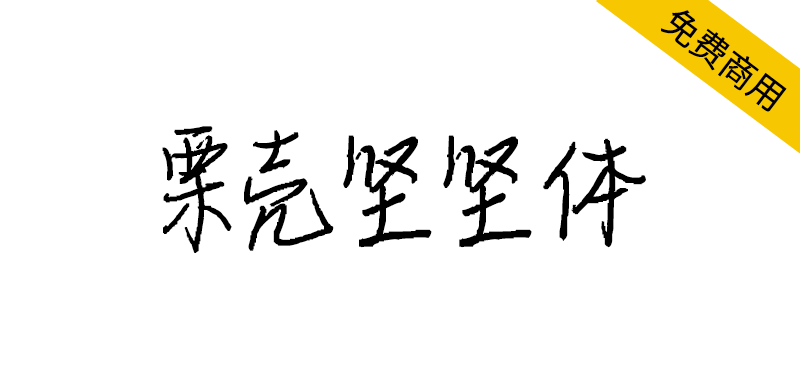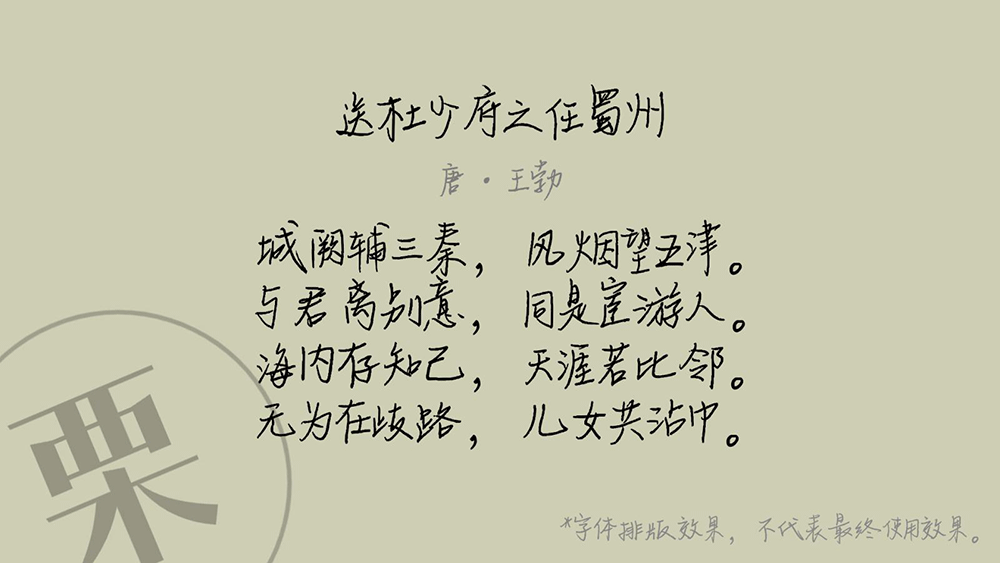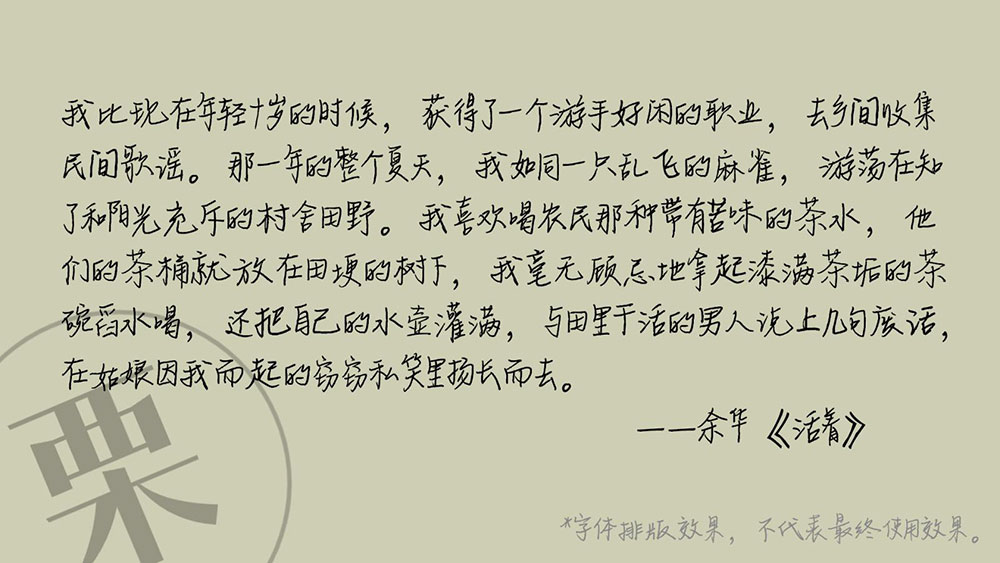
做一套字体,一直是我的梦想。曾经,和多家大厂字体制作公司试稿,但都未通过。究其原因,要么就是对字体不满意,要么就是他们的字库中已经包含类似风格的字体。于是,我便想自己做一套字体。24年8月,字体计划正式启动。这一套字体基于我自己的手写体来制作,按照GB/T2312-1980,共收录6763个汉字(附带数字、英文和标点符号等)。9月,所有字体完成纸质稿书写,经扫描导入电脑,通过后期处理软件进行填充、切片,再通过专业软件进行制作,为保证字体间距合适、阅读舒适性等,还对所有的字逐一地进行了二次人工校对。
耗时半年,2025年2月,经测试封装,栗壳坚坚体正式上线。目前,该字体已上线栗壳字库官网,网上对于字体制作的流程介绍甚少,且因为中文字库的工程量庞大繁琐,导致目前市面上的英文字库数量远大于中文字库。栗壳坚坚体作为一款在摸索阶段制作出来的字体,实属不易。该字体可以免费商用,无需取得授权。